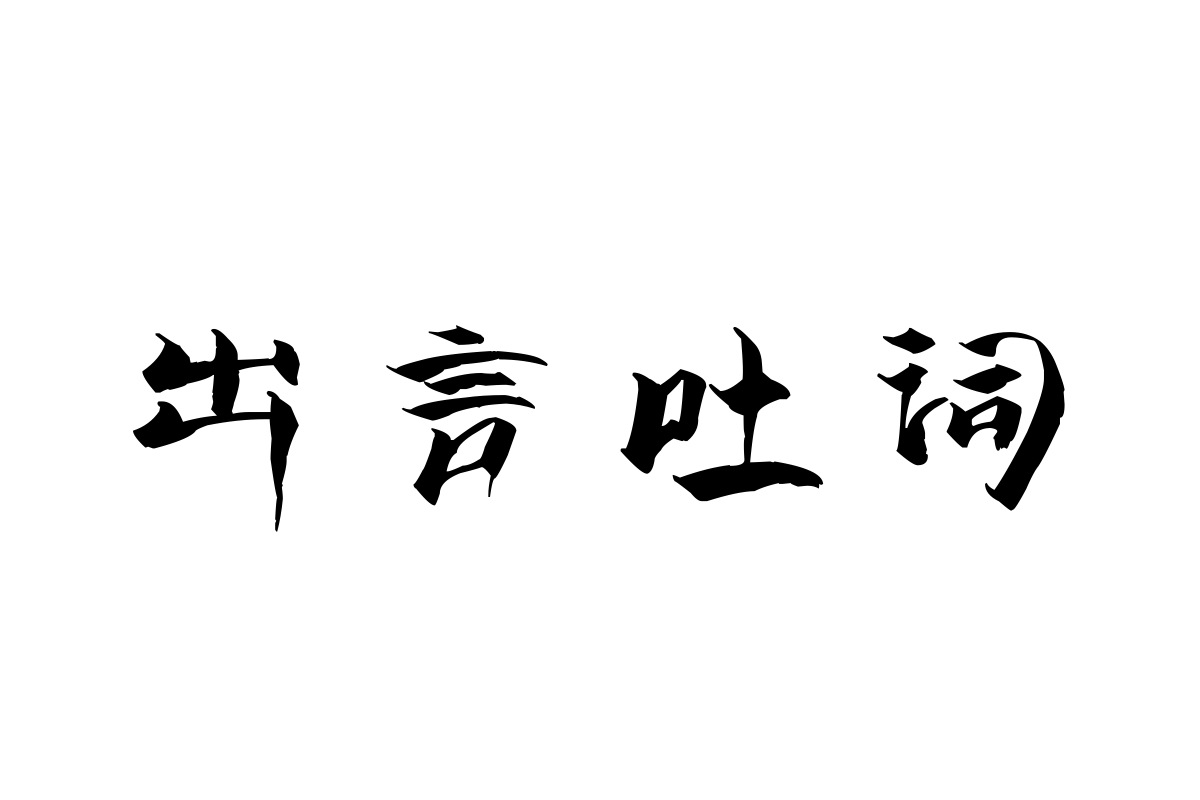
汉标东方不败字体是一种具有独特韵味的中文字体,由汉标公司设计。这款字体以其独特的字形和笔画结构,给人一种古典而优雅的感觉。它适用于各种需要展示传统文化和艺术氛围的场合,如广告、宣传册、海报等。
汉标东方不败字体的特点如下:
1. 字形优美:这款字体的字形线条流畅,结构紧凑,给人一种优美的视觉效果。
2. 笔画独特:与常见的汉字笔画相比,汉标东方不败字体的笔画更加独特,线条粗细变化丰富,增加了字体的艺术感。
3. 风格古典:汉标东方不败字体的设计灵感来源于古代书法艺术,因此整体风格呈现出一种古典而优雅的气息,适合用于展示传统文化和艺术氛围。
4. 适用范围广泛:这款字体适用于各种需要展示传统文化和艺术氛围的场合,如广告、宣传册、海报等。
总之,汉标东方不败字体是一款具有独特韵味的中文字体,适用于各种需要展示传统文化和艺术氛围的场合。